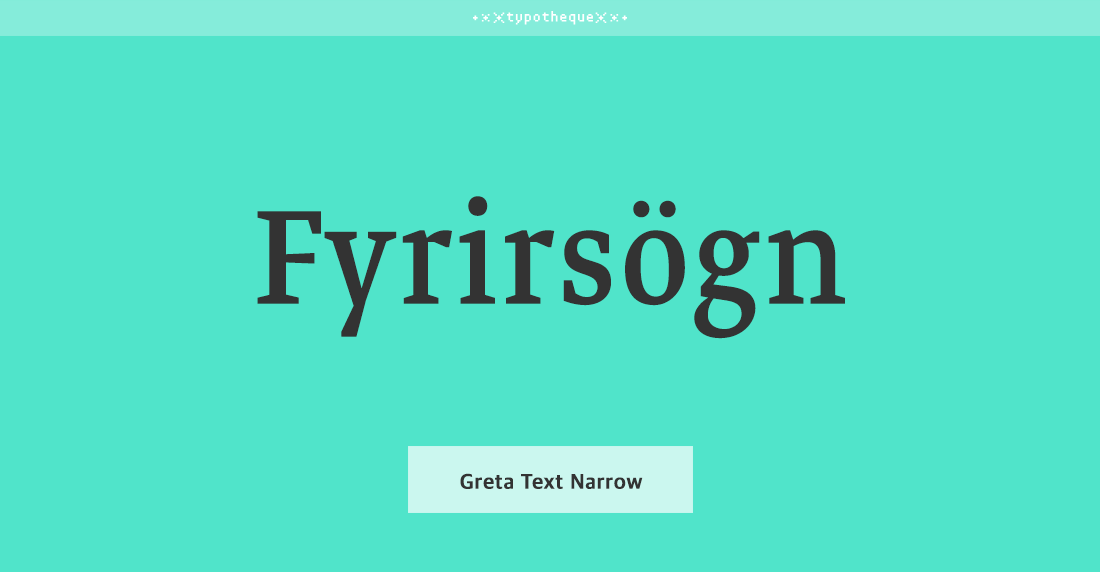
Greta Text Narrow Std
Greta Text Narrow Std는 특별히 신문 인쇄의 요구에 맞춰 설계된 공간 절약형 폰트이다.
4개의 웨이트로 이루어져 있으며 아주 작은 사이즈에서도 가독성과 사용성을 모두 확보할 수 있다.
- Nikola Djurek PeterBiľak